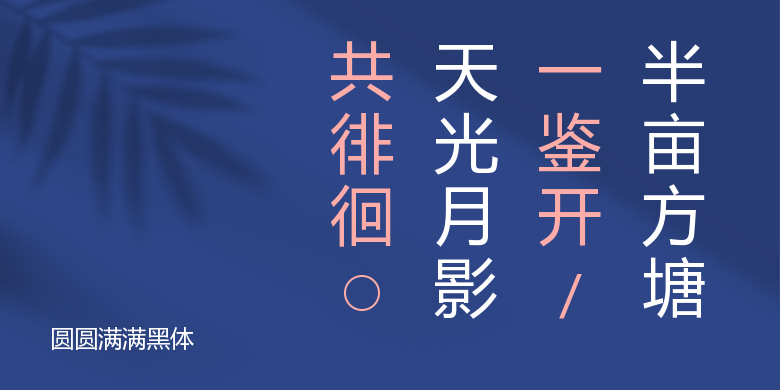
圆圆满满黑体
圆圆满满黑体,这款字体结构工整、笔画清晰,兼顾美观与易读性,适用于标题、正文、海报、包装、LOGO 等多种场景。字形优雅稳定,风格百搭耐看,适配日常排版与创意设计,让文字呈现更舒适、更具质感。圆圆满满黑体一笔一画,皆是细节,以均衡的比例、流畅的线条打造舒适视觉体验,字形端正大气,风格简约现代。无论是商业设计、品牌宣传还是日常排版,都能轻松驾驭,让文字更有格调与力量。圆圆满满黑体字体下载。